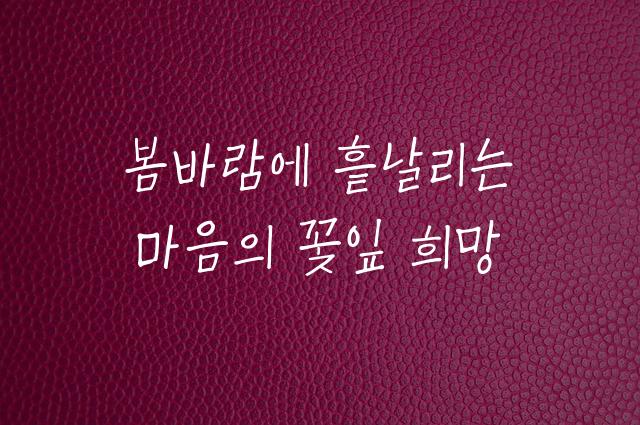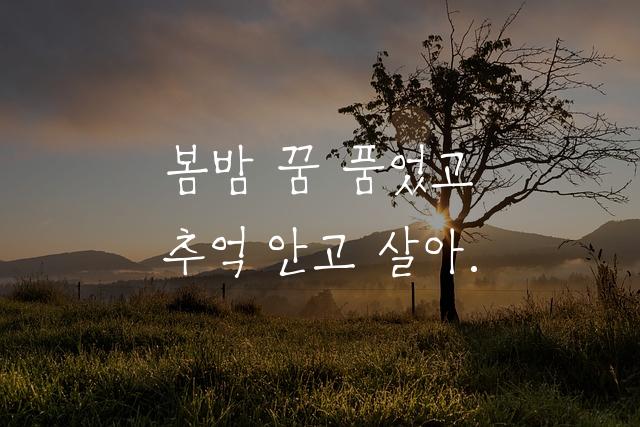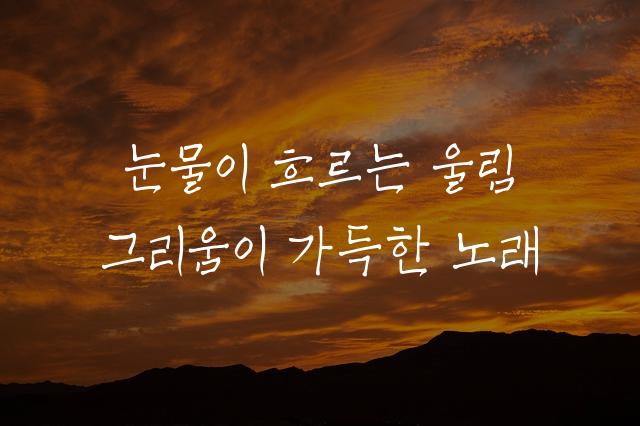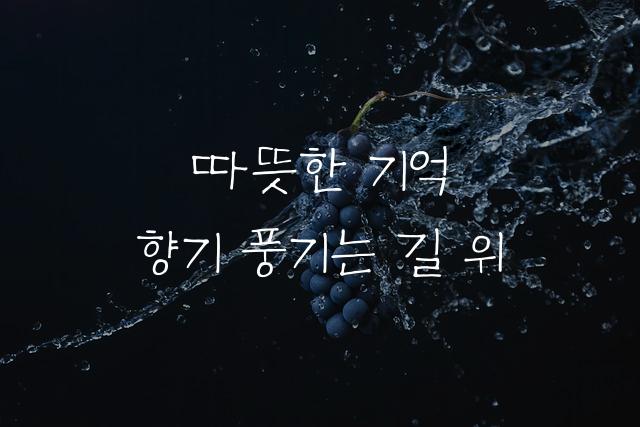
칠곡할매 김영분체는 삐뚤빼뚤하고 정감 있는 어른 손글씨 스타일의 폰트입니다. 따뜻한 인간미가 묻어나는 이 폰트는 독특한 개성과 전통적인 감성을 동시에 표현합니다.
칠곡할매 김영분체은(는)
손글씨, 감성적인, 부드러움 계열의 생김새를 가지고 있으며
인사말 카드, 카페 메뉴, 일기/편지 등에서 자주 활용되며, 효과적인 메시지 전달에 적합합니다.
이 폰트는 라이프스타일, 유아/가족, 커뮤니티 분야에 잘 어울리며,
따뜻한, 부드러운, 편안한 느낌을 담고 있는 것이 특징입니다.
이 폰트와 유사한 폰트로는 나눔손글씨 붓, 한나는 열한살, 서울한강체 등이 있어요. 함께 비교해 보시면 좋습니다!